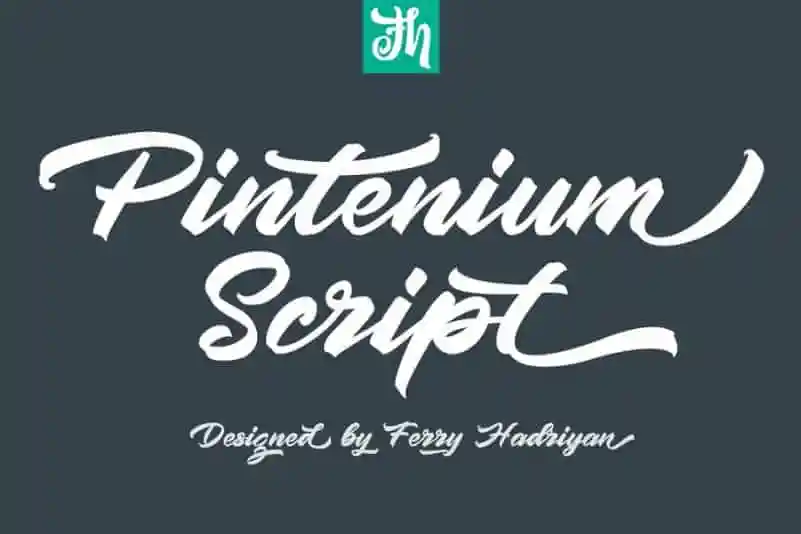
Pintenium Brush Font – Download Grátis
Introduzimos a Pintenium Brush Font, uma elegante tipografia chisqueira que transmite calor e leveza, perfeita para estilos vintage. O designer FHFont concebeu este tipo de letra como um fusão de Chique Script Brush com Estilo de Caneta à Mão, oferecendo numerosos recursos de fonte aberta. Esta fonte traz uma rica mistura de elegância e brilho, ideal para diversas aplicações. Seja em designs originais, design do elemento, convites ou eventos, camisetas personalizadas, logomarcas, selinhos, adesivos, ela se encaixa perfeitamente. A Pintenium Brush Font é uma escolha óbvia para aquelas pessoas que buscam um toque sofisticado e inovador em seu trabalho visual.